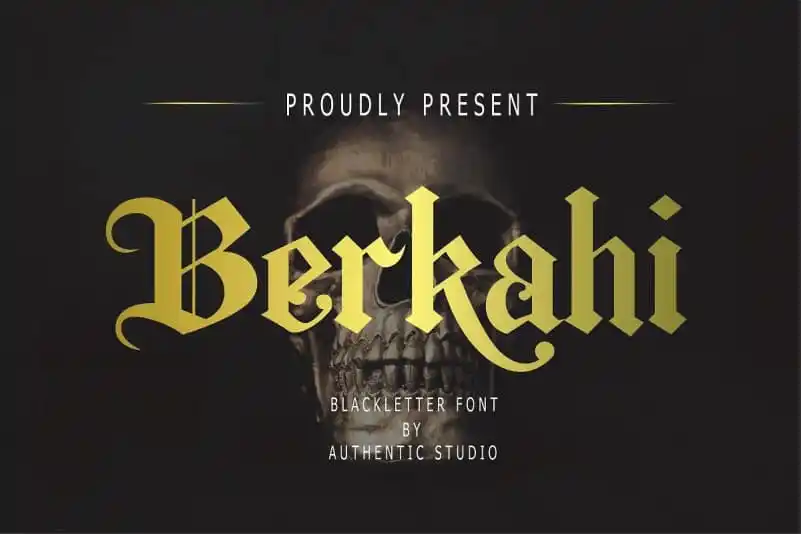
Berkahi Blackletter Font – Download Grátis
Introduzimos a Berkahi Blackletter Font. É uma tipografia inspirada nos estilos celta ou uncial. Ela carrega um estilo vintage único e bem peculiar, tornando-a perfeita para designs com ilustrações e como fonts de exibição. Foi desenvolvida pela Authentic Studio. Eu adoraria apresentá-la, a fonte Just Imagine, que traz uma sensação clássica e elegante, um toque vintage e mágico, com um charme único do gótico blackletter para os seus designs. Ideal para tattoos, roupas, etiquetas e embalagens, marca, ou qualquer projeto em temática gothic! Espero que você tenha gostado. Esta fonte de estilo Blackletter vem à perfeita complementação para trabalhos inspirados no gótico. Suas linhas delicadas e tridimensionais criam um visual elegante e sofisticado, adequado tanto para o uso em aplicações digitais quanto físicas. A Berkahi Blackletter oferece uma ampla variedade de pesos e estilos que permitem adaptá-la a diversos tipos de projetos. A Berkahi Blackletter traz consigo um toque mágico e vintage, combinando elementos elegantes com o charme do gótico. É perfeitamente adequada para designs onde um toque histórico é desejado ou mesmo para aplicativos digitais que valorizam uma aparência clássica e sofisticada. Esta fonte também pode ser uma ótima escolha para projetos em torno de temas relacionados ao passado. Por exemplo, estilos como história, arquitetura gótica, ilustração medieval ou até mesmo arte contemporânea inspirada no estilo antigo podem se beneficiar da utilização desta fonte. A Berkahi Blackletter também é adequada para uso em aplicações de marca e identidade visual. O seu design elegante pode ser incorporado nas letras do logo, nos elementos de marca como a embalagem ou até mesmo os rótulos de produtos, adicionando um toque único e sofisticado ao seu design. Se você está procurando por uma fonte que se encaixa perfeitamente em um projeto com estilo gótico, então a Berkahi Blackletter é definitivamente o tipo certo. Ela oferece uma variedade de opções para que possa adaptá-la a diferentes formatos e tamanhos, garantindo que sempre esteja ao alcance quando você precisar dela. Estas são apenas algumas das muitas maneiras em que a Berkahi Blackletter pode enriquecer seus projetos. Não perca tempo e descubra como esta fonte pode transformar seu design de uma forma única e elegante, com um toque vintage e mágico do gótico blackletter.